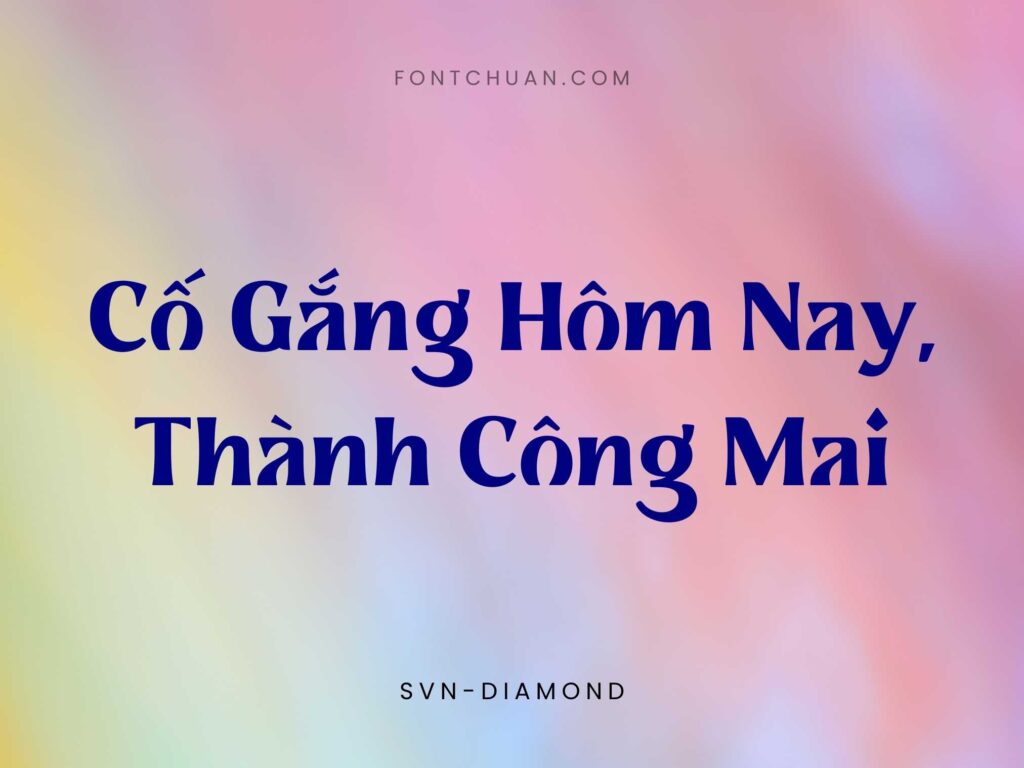
Font SVN Diamond Việt Hóa
Tác giả Font: Zamroni Hamzah
Diamond là một font chữ thuộc thể loại Display, được thiết kế bởi Zamroni Hamzah và phát hành bởi Sensatype. Font này mang phong cách cổ điển và độc đáo, phù hợp cho các dự án thiết kế liên quan đến thương hiệu, logo, thiệp cưới, bài đăng trên mạng xã hội, quảng cáo và bao bì sản phẩm. Font đã được Việt hóa để hỗ trợ tiếng Việt bởi STYLEno.1 Fonts, đồng thời hỗ trợ nhiều ngôn ngữ khác, giúp mở rộng phạm vi sử dụng trên toàn cầu. Font này được chia sẻ miễn phí cho mục đích sử dụng cá nhân; để sử dụng cho mục đích thương mại, bạn nên mua bản quyền từ nhà phát hành.
Đặc điểm thiết kế của Diamond bao gồm các đường cong độc đáo, tạo nên sự nổi bật và dễ đọc trong các ứng dụng như tiêu đề, logo, bao bì sản phẩm và các dự án sáng tạo khác. Các ngành nghề phù hợp bao gồm quảng cáo, nghệ thuật và thiết kế đồ họa.